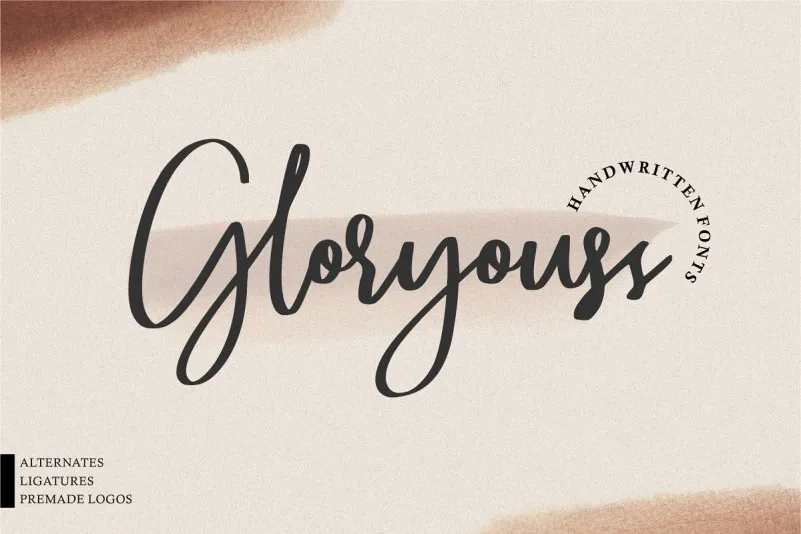
Gloryouss Script Font
A Gloryouss Script Font é uma opção irresistível para designers buscando uma fonte escrita a mão que transmite sofisticação e elegância. Embora seja natural e moderna, sua curva encantadora assegura um toque refinado nas criações. Ideal para logos, convites, notas de carta, estilos de casamento, posts no Facebook, anúncios, embalagens de produtos, designs de produto, rótulos, fotografias e até mesmo para marca d’água em eventos especiais ou qualquer aplicação que busque um visual luxuoso. Este fonte perfeita para quem procura uma escrita agradável e sofisticada, que traz vida e personalidade a qualquer projeto. Engane-se só se não deseja experimentar a exuberância de sua curva elegante na sua próxima criação!